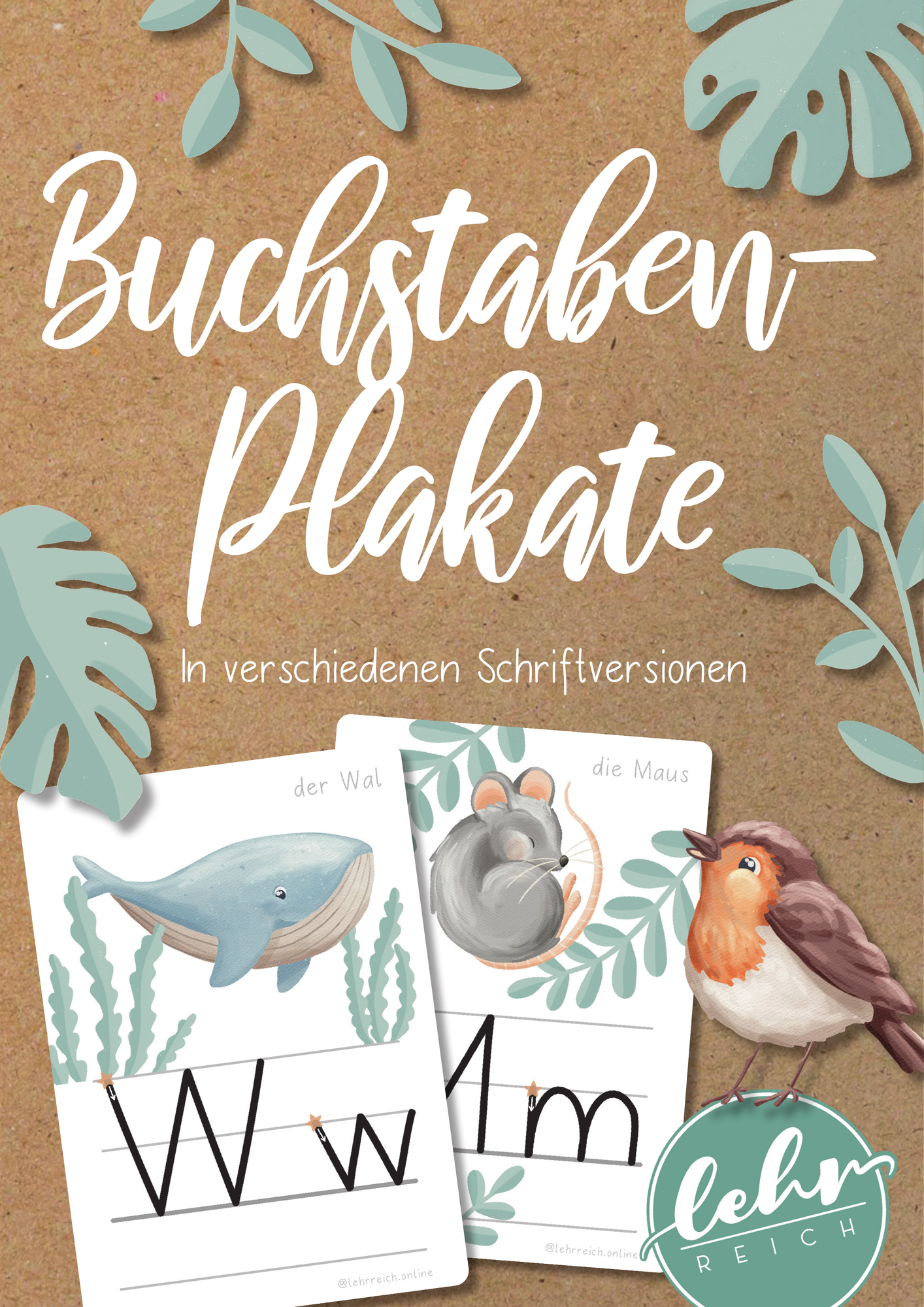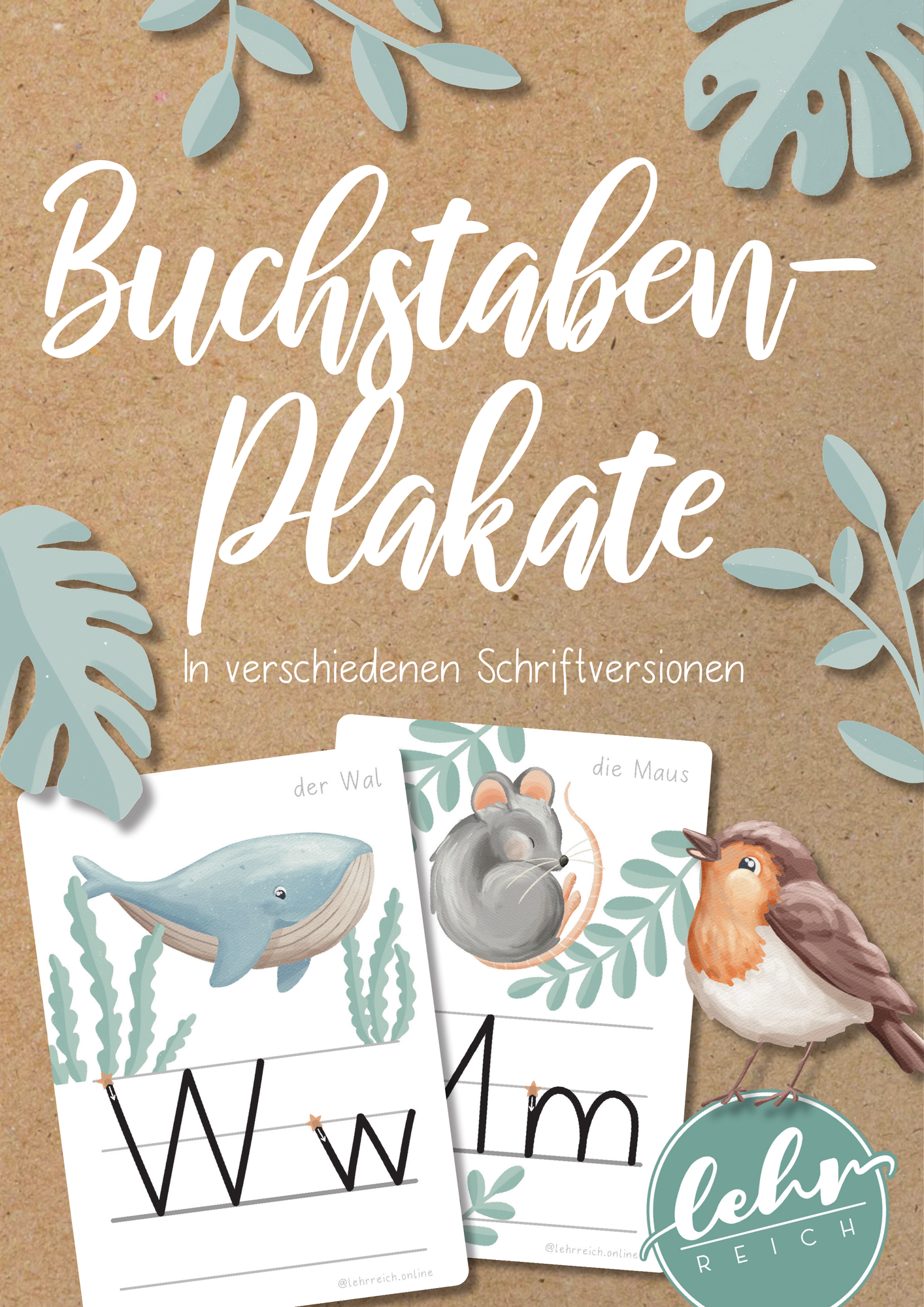
Poster - Buchstaben Plakate - Alphabet in verschiedene Schriftarten - lehrreich - Deckblatt
Die Buchstabenplakate sollen den Kindern helfen, sich die Buchstaben bzw. Laute einzuprägen. Im Klassenzimmer aufgehängt können sie als Anlauttabelle genutzt werden und zeigen gleichzeitig den richtigen Schreibablauf. Jeder Buchstabe bzw. Laut wird von einem Tier repräsentiert, während die Vokale von zwei Tieren dargestellt werden, um die unterschiedlichen Vokallaute in der deutschen Sprache anschaulich zu vermitteln.
Das Alphabet ist in verschiedenen Ausführungen vorhanden, um den Bedürfnissen unterschiedlicher Schriftversionen im deutschsprachigen Raum gerecht zu werden.
• Druckschrift
• Schweizer Basisschrift
• Schreibschrift (Österreich)
• Deutsche Schulausgangsschrift (SAS)
Buchstaben Plakate - Alphabet in verschiedene Schriftarten